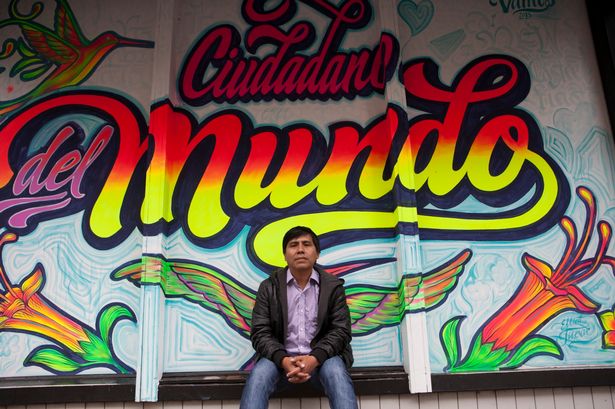
Para empezar esta serie de entrevistas tenemos a uno de los artistas con mayor proyección a nivel mundial de toda américa latina, Elliot Tupac. Y es que este peruano de 38 años es mundialmente famoso por intervenir paredes de todo el planeta, creando llamativos y coloridos murales:
Tu trabajo tiene un trasfondo muy interesante ya que en ellos podemos ver una gran influencia de la cultura popular de PerĂş, cuĂ©ntanos, por favor, de donde viene tu trabajo, que es el estilo “chicha” y toda esa increĂble esencia del que se nutre tu trabajo.
Mi trabajo tiene mucha influencia del “Cartel Chicha”, un oficio que surgiĂł en los 80s, siendo mi padre uno de los pioneros junto con otras personas. El Cartel Chicha surgiĂł bajo la necesidad de desarrollar un medio de comunicaciĂłn barato y eficaz, toda esta producciĂłn de carteles estaban destinados a promocionar eventos de mĂşsica tropical “Chicha”. El sistema es muy sencillo, dibujar de manera personalizada cada nombre de grupo y demás informaciĂłn relevante del evento, hacer el recorte e inmediatamente imprimir directamente como si fuera una especie de stencil, ya que el diseñador o el impresor tenĂa la libertad de crear y colocar la cantidad de colores neones que sea necesario.
Los colores Neones son fundamentales en la creaciĂłn de los carteles, este oficio lo desarrollaron personas como mi padre que provenĂan de la Sierra central Huancayo, donde las vestimentas tĂpicas siempre tienen una exaltaciĂłn del uso de estos colores iridiscentes. Yo en lo particular tengo la influencia cercana de mi padre que fue “impresor de cartel” y comunicador social vinculado a temas culturales “locutor de radio” y de mi madre que tambiĂ©n fue artesana del “bordado wanka”
CĂłmo es valorado este estilo dentro de PerĂş? ¿La gente corriente suele entender y valorar tu trabajo?
Mi trabajo en Lima se ha posicionado de manera interesante, pues se ha colocado en las distintas esferas sociales, desde un público sencillo económicamente hasta un público con posiciones más cómodas. Me preocupe siempre que la estética del color y dibujo de las letras puedan servirme como un medio para utilizar un discurso más transversal socialmente. Es satisfactorio ver que tu trabajo no distingue, no discrimina, sino todo lo contrario, une, vincula, es como un puente de acercamiento social.
Además siempre tengo la obsesiĂłn de mejorar la calidad de las letras, sus proporciones, tĂ©cnicamente me preocupo mucho de las teorĂas de la TipografĂa porque me encanta y lo descubrĂ por este oficio de dibujador de letras. Me gusta hacer Lettering pensando en TipografĂa.
Procuro hacer mi oficio lo mejor que puedo, soy diseñador, impresor, muralista, realizó conferencias y talleres. Toda esta suma hace que mi trabajo pueda tener distintas opciones de vinculación con la gente, desde gente especializada a gente común pero con acercamiento visual y emocional a la obra.
Trabajo entre hacer diseños para marcas grandes, como pintar unos dĂas en la calle como cualquier mortal.
Hablando de la situaciĂłn de la letra en el pasado, presente y futuro, tu trabajo en cierta medida rescata una increĂble cultura pasada y la consigue traer al presente ¿CĂłmo has notado que el gran pĂşblico ha asumido tu trabajo en cuanto a situarlo en este mundo tan tecnolĂłgico que nos rodea?
Creo que en mi caso este proceso natural con el trabajo ha hecho que el romance con lo analógico sea muy honesto, del mismo modo que también se vincula a lo tecnológico por un tema inevitable de nuestra época, seria mentir solo ensalzar lo analógico, teniendo tantas ventajas tecnológicas.
Mi interés más que el soporte tiene que ver con el hacer lo mejor que puedo en cada situación que me toca como diseñador de letras.
Yo tengo mucho cuidado con el tema de revalorar lo analĂłgico, entender hasta que punto es justo y en quĂ© momento se pone en la lĂnea ambigua, No todo lo analĂłgico es bueno, hay cosas desastrosas en estos temas analĂłgicos. Creo fielmente que eso es una circunstancia pasajera, es como cuando empieza el mes de los circos, es cĂclico todo. Lo importante es que tomemos nuestro oficio con profesionalismo y seriedad.
Detrás de tus trabajos podemos encontrar una especial atenciĂłn por el lettering, al trabajo a mano alzada, a la composiciĂłn tipográfica... ¿Esta atenciĂłn a la letra es algo que ya venĂa con el estilo que tu trabajas o es algo que tĂş le has aportado? ¿cuánto peso tiene la letra en tus diseños?
Tienes razón, mis diseños pueden resumirse en DISEÑO LETTERING, PENSANDO EN TIPOGRAFIA.
He tenido dos maestros y eso ha sido un privilegio, Mi padre y mi hermano, ambos muy obsesionados con el dibujo y ambos con estilos diferentes; bajo esa circunstancia yo tambiĂ©n tengo otro estilo, me encanta ver que en mi familia somos tres dibujando letras y cada uno tiene distinta sensibilidad al trazar las lĂneas para dibujar letras.
Desde niño he visto muchas transformaciones visuales en temas de diseño y siempre será asĂ.